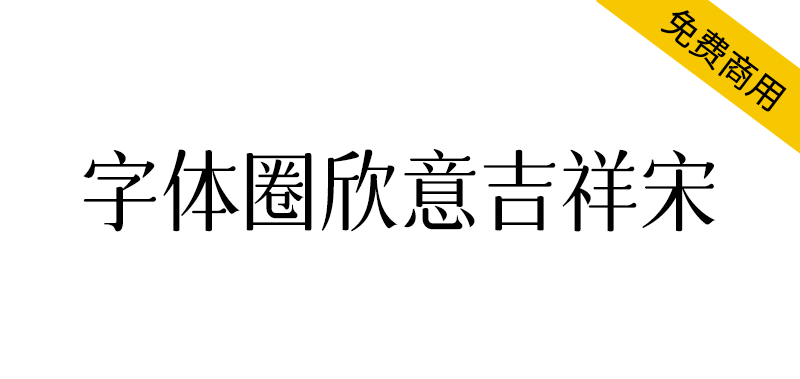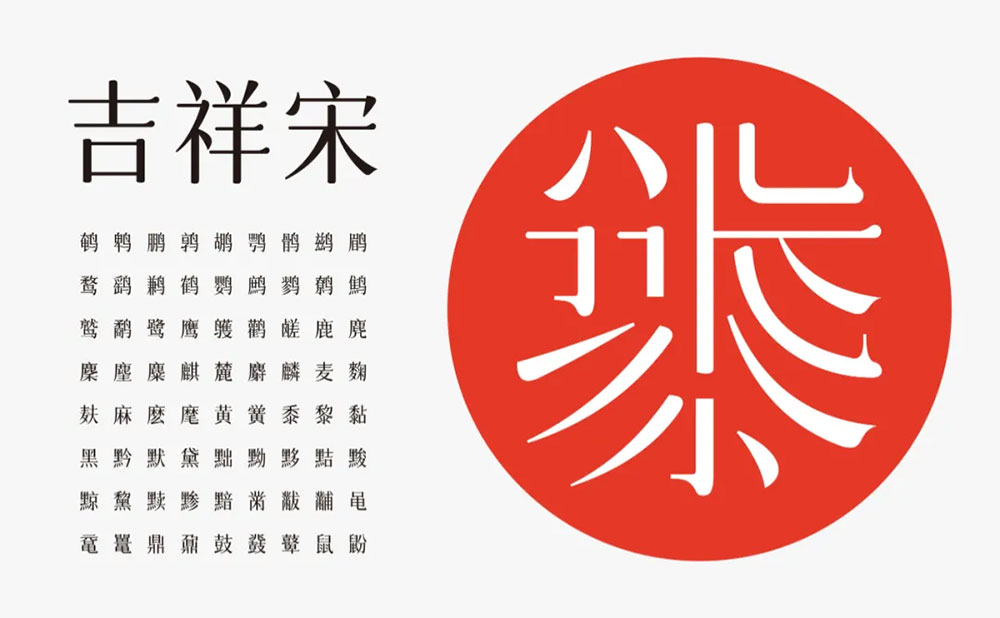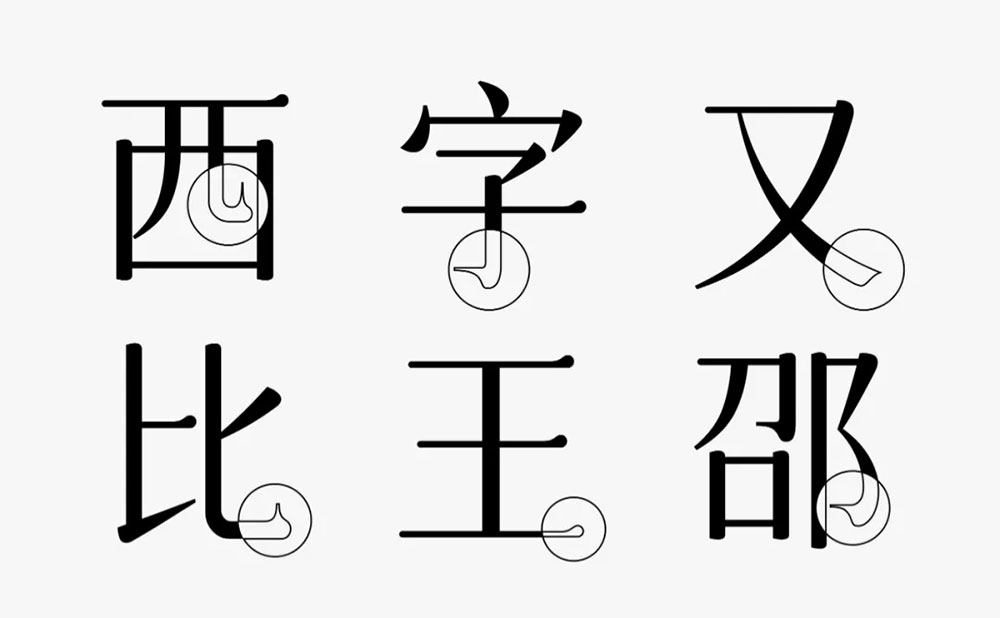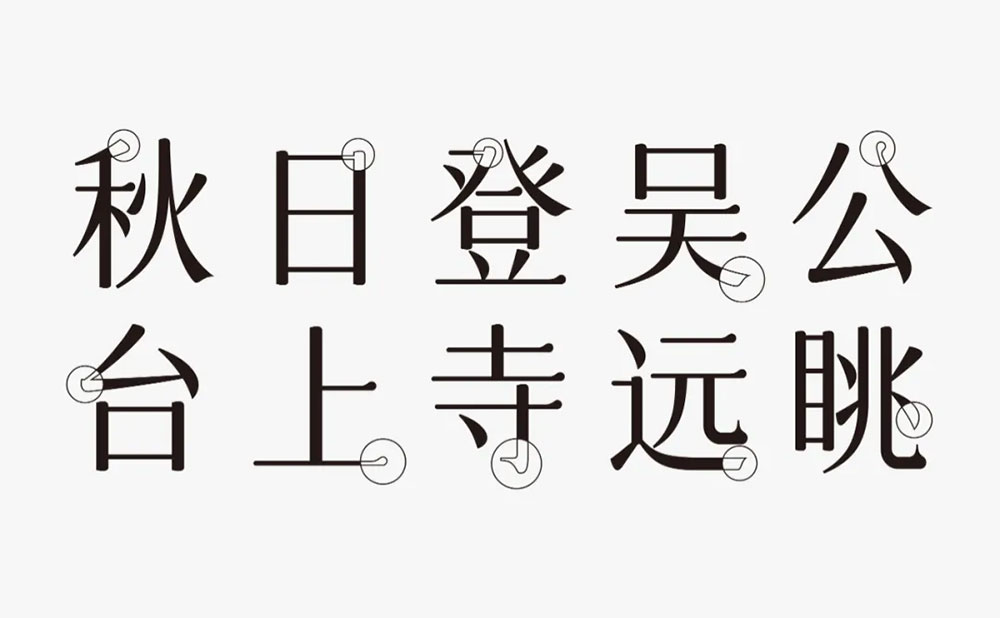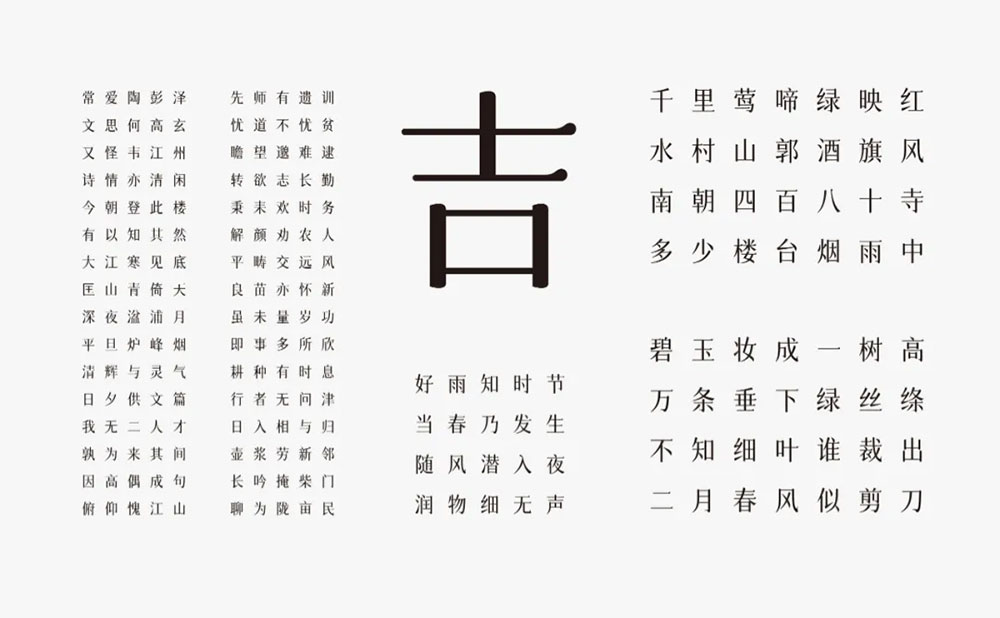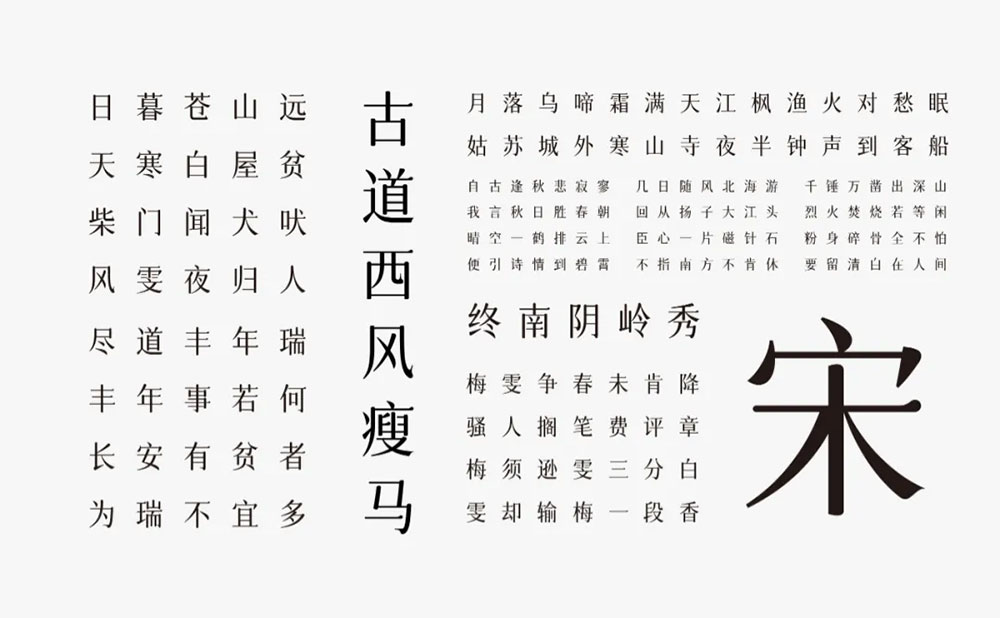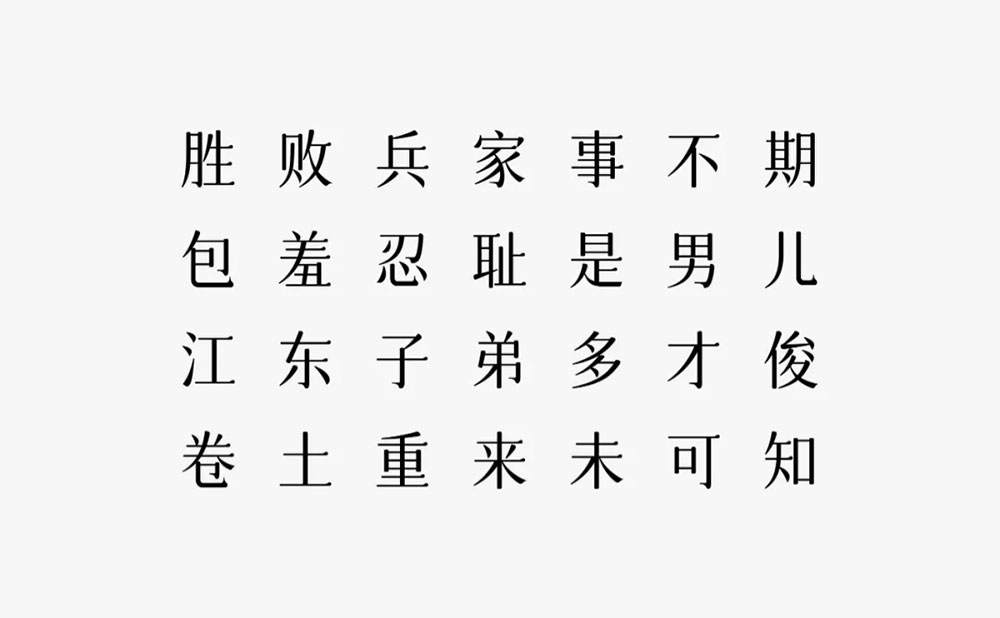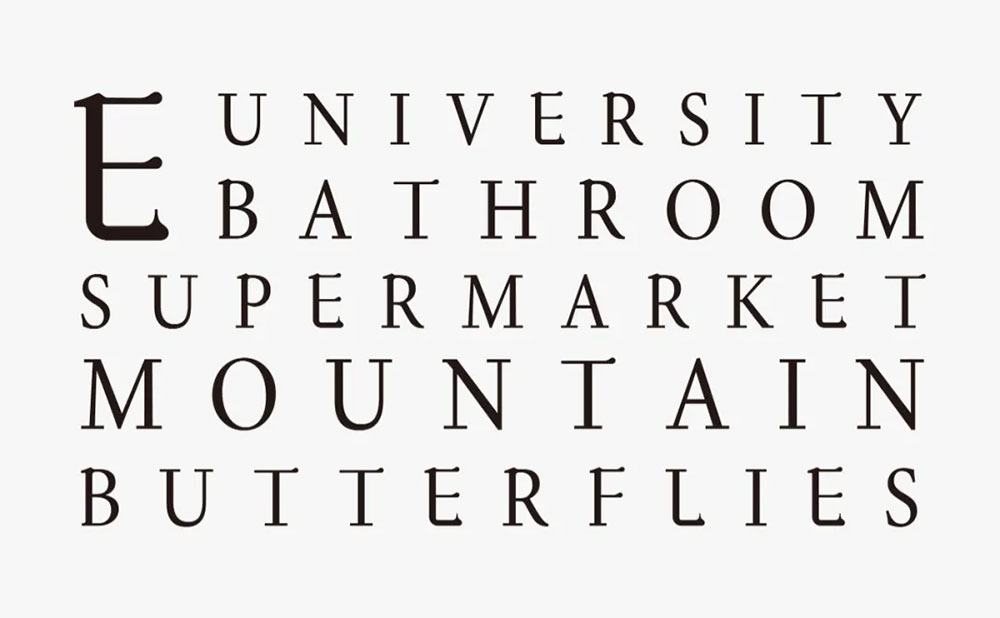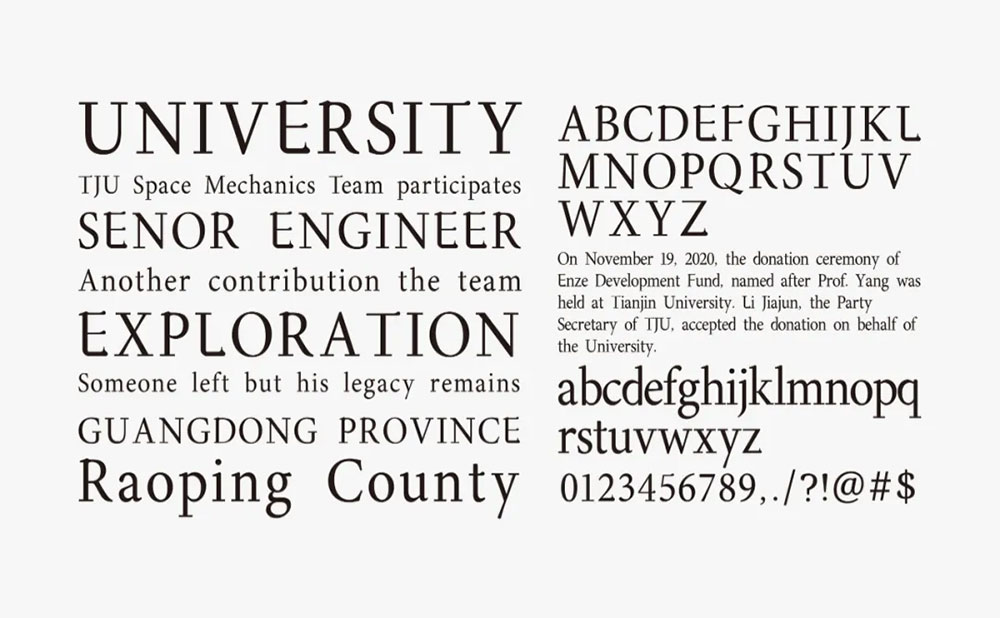
字体圈欣意吉祥宋是一套宋体风格的标题字体,风格整体偏圆润古风,目前市场上免费商用的宋体字,除了思源宋体,好像就是思源宋体的修改版,没有专门设计风格的宋体字。这套字涵盖国家GB2312编码标准的6763个中文字符,52个英文字符,10个阿拉伯数字,若干个标点符号,按需添加若干生僻字,共7000余字符。
整套字形视觉感偏瘦高,宽高比例为4:5,尝试过1:1甚至更矮的比例,不够优雅,因为像这种圆润纤细古风女性化的字体,都是比较修长才好看,最后才决定4:5这个近乎完美的比例。
这款字风格圆润,比如横画开头及结尾由传统字体的三角尖凸变成较圆润的风格,竖画由三角尖凸也变成圆润无尖凸风格,竖勾撇捺点的笔画同理,2021,祝您吉祥!